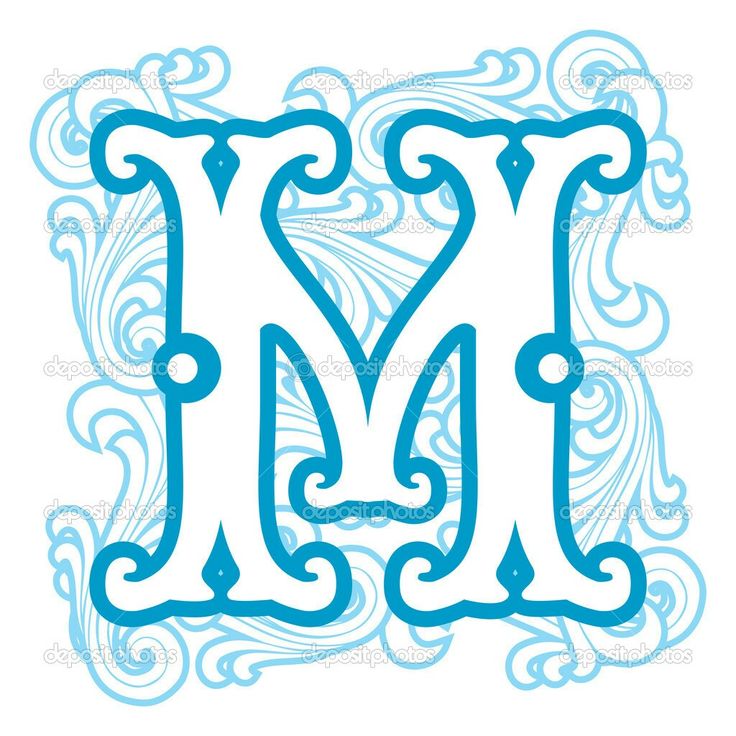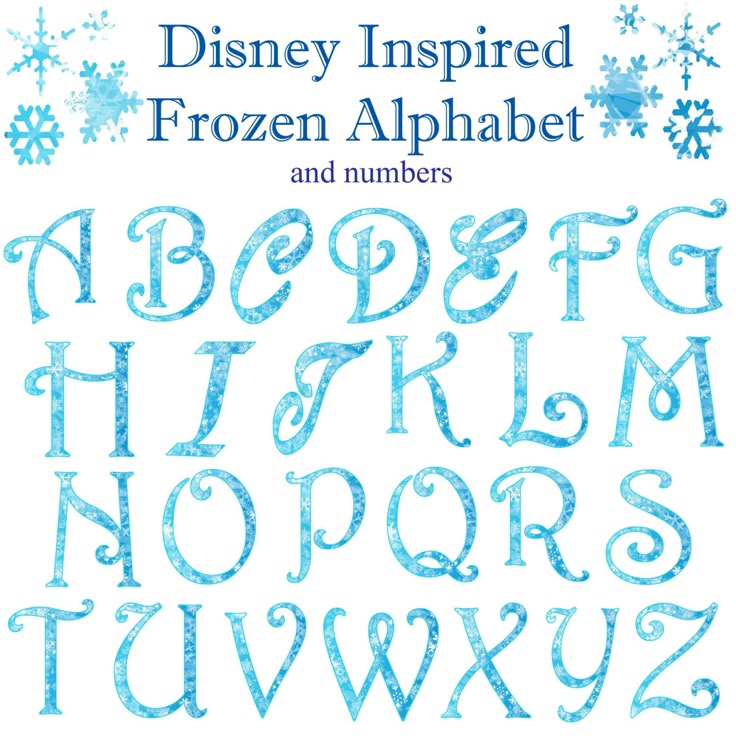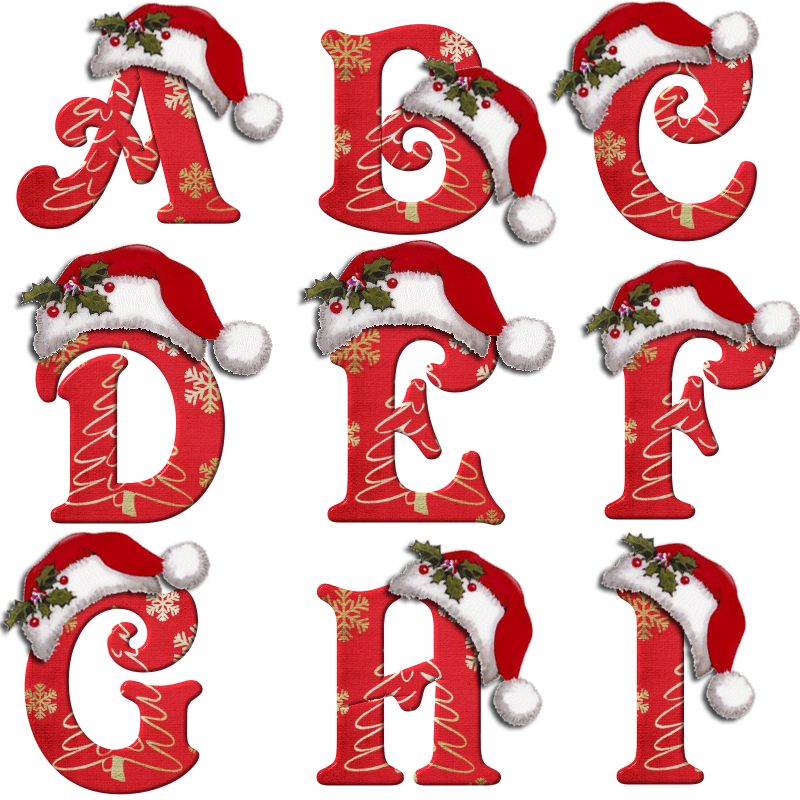
Зимний русский шрифт: Новогодние шрифты, скачать бесплатно (русские рождественские шрифты на Facefont)
Вы хотите сделать действительно впечатляющую открытку или дизайн для грядущего праздничного сезона?
Порой эта задача может застать врасплох. Какие образы использовать? Какие цвета подойдут лучше всего? А что насчет шрифтов? К счастью для вас, мы собрали 30 отличных вариантов, вдохновленных Новым годом и Рождеством. 15 латинских шрифтов и 15 шрифтов на кириллице (есть возможность использовать русский язык).
Латинские шрифты
1. One Starry Night
Это очень приятный шрифт, похожий на рукописный. Встречающиеся в его символах вихри и завитушки придают ему энергичности, а тонкость букв делает легким и воздушным.
2. Metro Retro NF
Рельефная форма и пунктирные линии из точек придают этому шрифту кружевной вид. В нем присутствуют кубические, но утонченные формы, а также нотки ретро-стиля (отсюда и название). Благодаря кружевному орнаменту шрифт не кажется устаревшим и приобретает праздничное настроение.
3. Sentinel
Этот крученый шрифт выглядит великолепно. Заглавная буква по классике оформлена гораздо выразительнее остальных, что сразу выделяет начало предложения. Данный шрифт встречался в старых рождественских книжках, поэтому он наверняка вызовет самые приятные воспоминания.
4. Chopin Script
Каллиграфические шрифты всегда отлично подходят для праздничного дизайна, и Chopin Script не является исключением. Тонкие буквы в сочетании с аккуратными акцентными линиями создают по-настоящему элегантную гарнитуру, которая будет выглядеть уместно почти на всех рождественских открытках.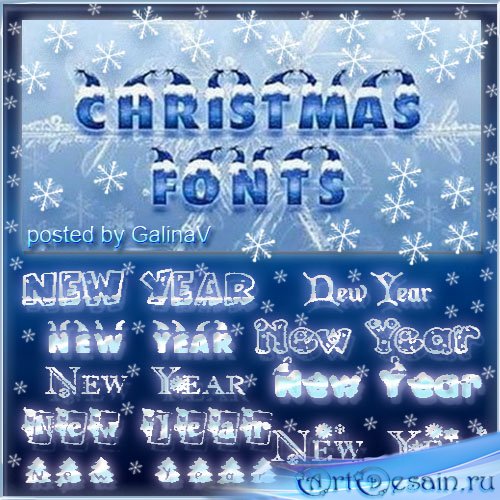
5. Mountains of Christmas
Неряшливость этого шрифта создает игривую и беззаботную атмосферу. Тонкие засечки в сочетании с мягким изгибом придают ему уникальный характер и прекрасно подойдут для иллюстраций на праздничную тематику.
6. St. Nicholas
Легкая рельефность этого шрифта придает ему неповторимый зимний облик. Строгие буквы смягчаются вырезами, напоминающими ямки в снегу. Они создают приятный контраст, который компенсируется акцентными завихрениями на заглавных буквах.
7. Harrington
Этот шрифт — старая добрая классика. Он чистый, но в то же время имеет декоративные акценты с небольшими наклонами и изгибами. Гарнитура обладает уникальным характером и хорошо подходит для заголовков.
8. Alex Brush
Широкие буквы и толстые линии делают этот шрифт легко читаемым.
Он идеально подходит как для заголовков, так и для короткого основного текста.
9. Hand Stockyard Font
Этот красивый шрифт будто написан кистью. Его нежная текстура и быстрые штрихи придают ему элегантный, но при этом не чересчур вычурный вид. Он имитирует настоящий почерк, что всегда идет на пользу праздничному дизайну.
10. Harbell
Подчеркните заголовок вашего рождественского дизайна этим смелым каллиграфическим шрифтом, будто написанным кистью. Обязательно используйте его в сочетании с простой гарнитурой с засечками, чтобы уравновесить дизайн.
11. Nickelodeon
Nickelodeon — это красивый, тонкий и незамысловатый шрифт. Простые засечки и стремительные изгибы букв придают ему индивидуальность. Этот невероятно сдержанный шрифт хорош как сам по себе, так и в сочетании с другими гарнитурами.
12.
Sunny Winter in Texas
Sunny Winter — очень тонкий, но притягательный шрифт. Он кажется самобытным и рукописным, создает приятную атмосферу и хорошо смотрится в паре с более жирным акцентным шрифтом.
13. Holleigh Caps
Этот элегантный и женственный шрифт украшен остролистом — одним из традиционных символов Рождества. Он полностью прописной, но буквы все равно хорошо сочетаются друг с другом благодаря своей тонкой и нежной структуре.
14. Landliebe
Очаруйте читателей своих пожеланий нестандартным, приземленным шрифтом. Landliebe дополнит как традиционный, так и эксцентричный рождественский дизайн.
15. Candy Cane
Этот задорный шрифт оформлен в виде загнутых карамельных тросточек. В конце концов, это один из главных символов рождественских праздников! Плавность закругленных краев прекрасно сочетается со сложной и динамичной штриховкой и помогает смягчить ее.
Кириллические шрифты
16. A_BraggaStars